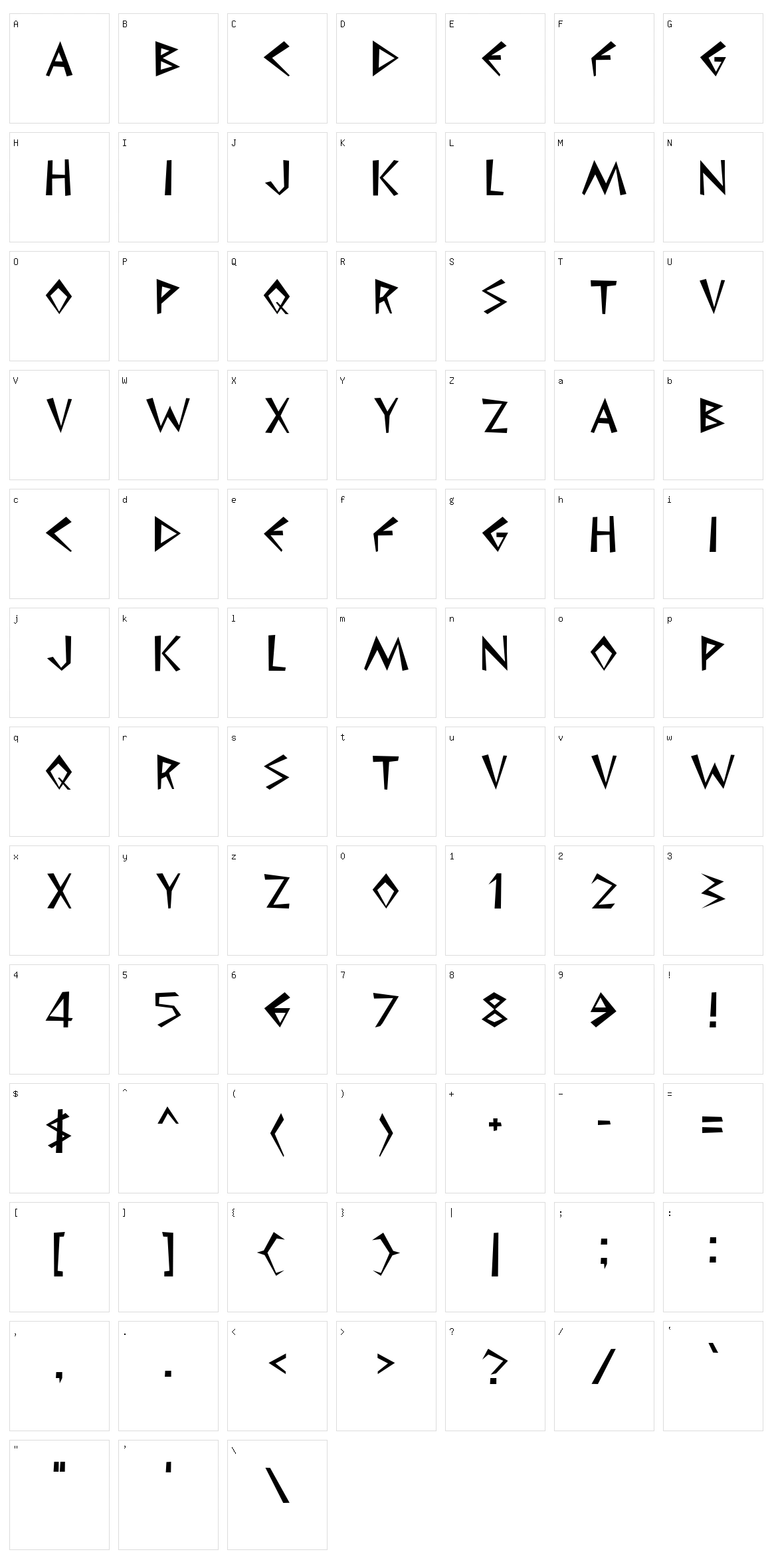
x CLEOPATRA FONT x
x LIZ TAYLOR COLLECTION x
Font name: LA GATTA sul TETTO che SCOTTA (Liz Taylor Collection) - Latin Decorative font (versione 1.0)
Type designer: P. A. Vannucci
CLEOPATRA font: direttamente dal film diretto da Joseph L. Mankiewkz,interpretato
da una indimenticabile LIZ TAYLOR e da Richard burton,il font inedito per tutti gli estimatori
del film. Da notare il ritocco necessario in Photoshop per conferire, alla titolazione, l'originale bordatura.
CLEOPATRA font: directly from the Best movie by Joseph L. Mankiewkz, with LIZ TAYLOR and RICHARD BURTON,
the original font for all lovers. Use ADOBE Photoshop for the original border from title.